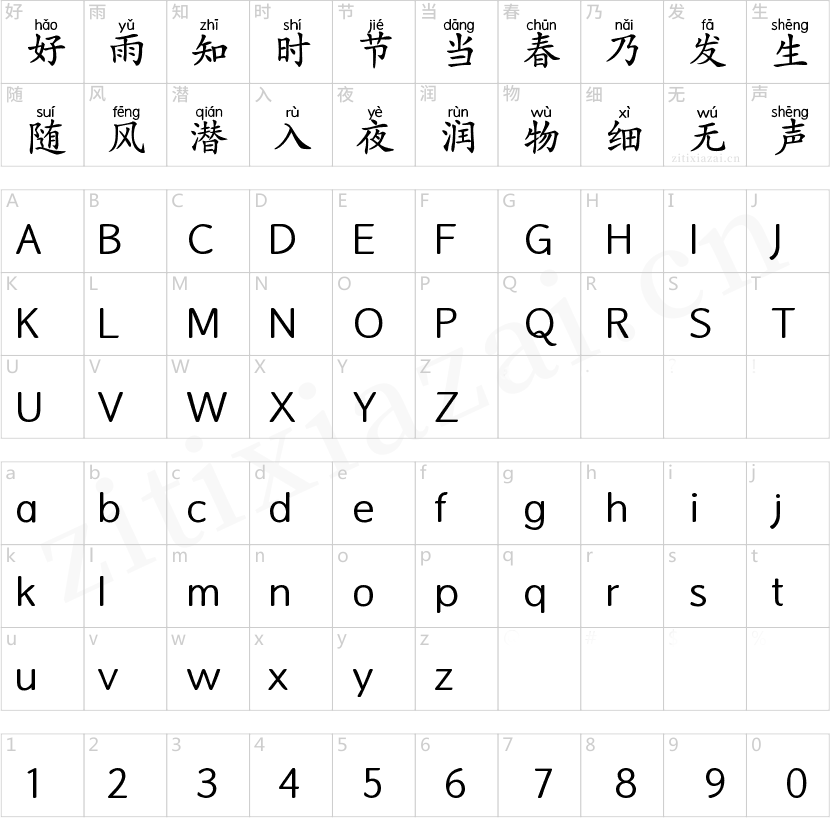
Aa楷书拼音
Aa楷书拼音字体
Aa楷书拼音是一款非常具有艺术性的字体,它的设计灵感来源于对古典艺术的研究,同时又融入了现代字体设计的元素。字形优美,笔画粗细变化自然,给人以大气、典雅的感觉。Aa楷书拼音是一款既传统又现代的字体,它的设计充满艺术感,美观大方,实用性也非常强。无论是对于设计师还是对于普通读者来说,都是一种非常不错的字体选择。Aa楷书拼音适合用于具有艺术感的场合,比如海报、宣传单张、书籍封面等。由于其字形流畅且具有动态感,也适合用于大量的文本排版,如报纸、杂志等。